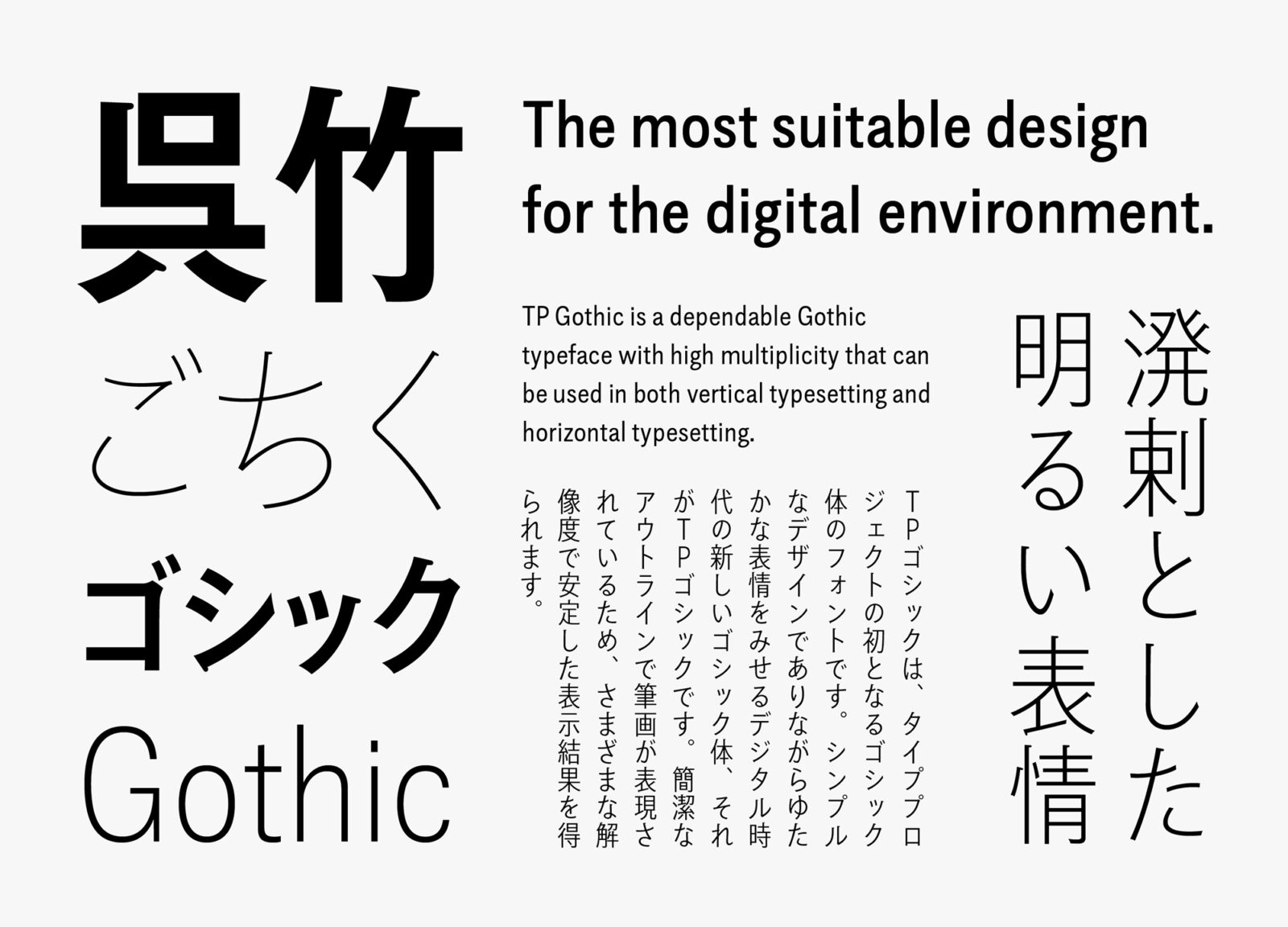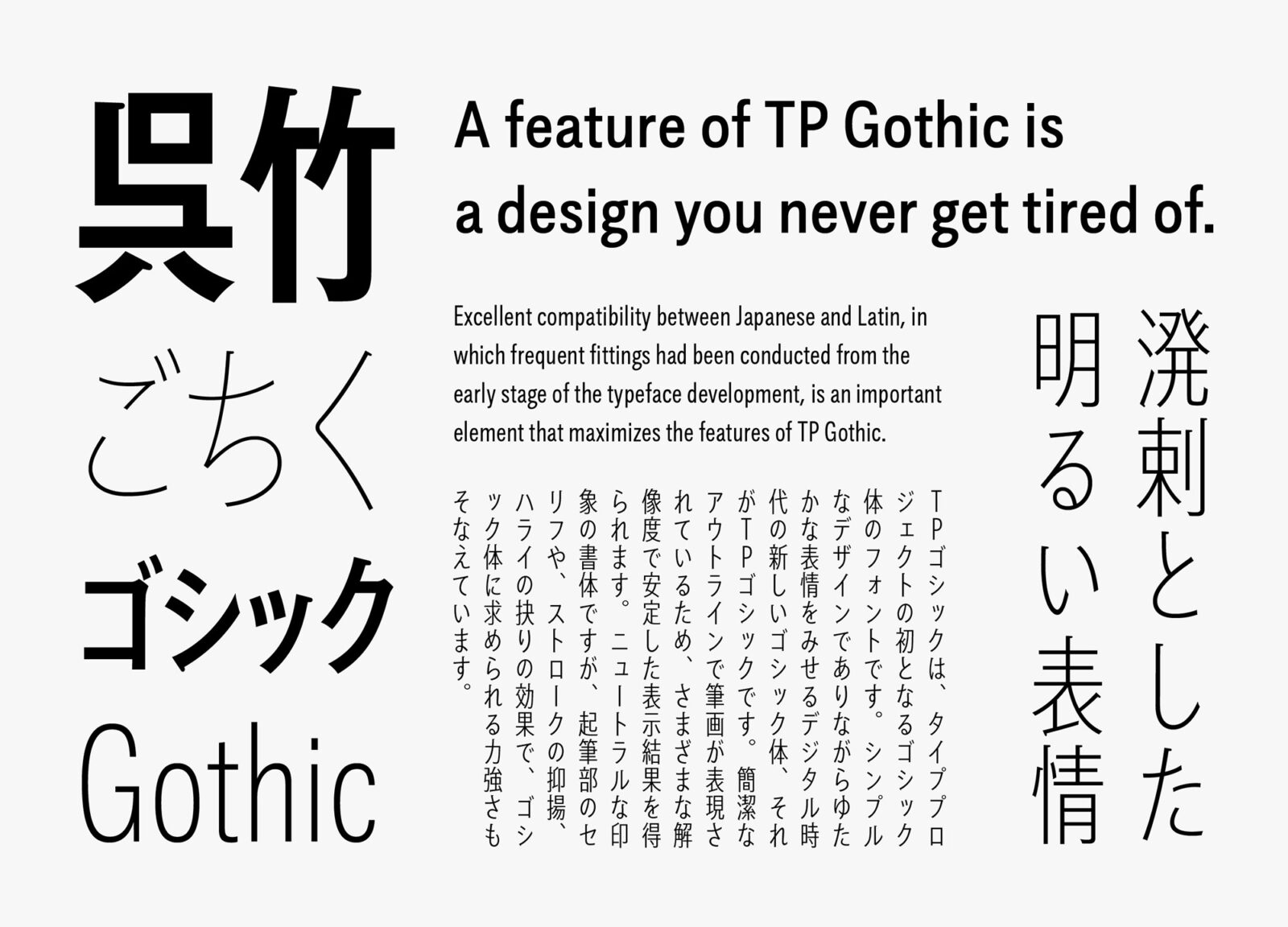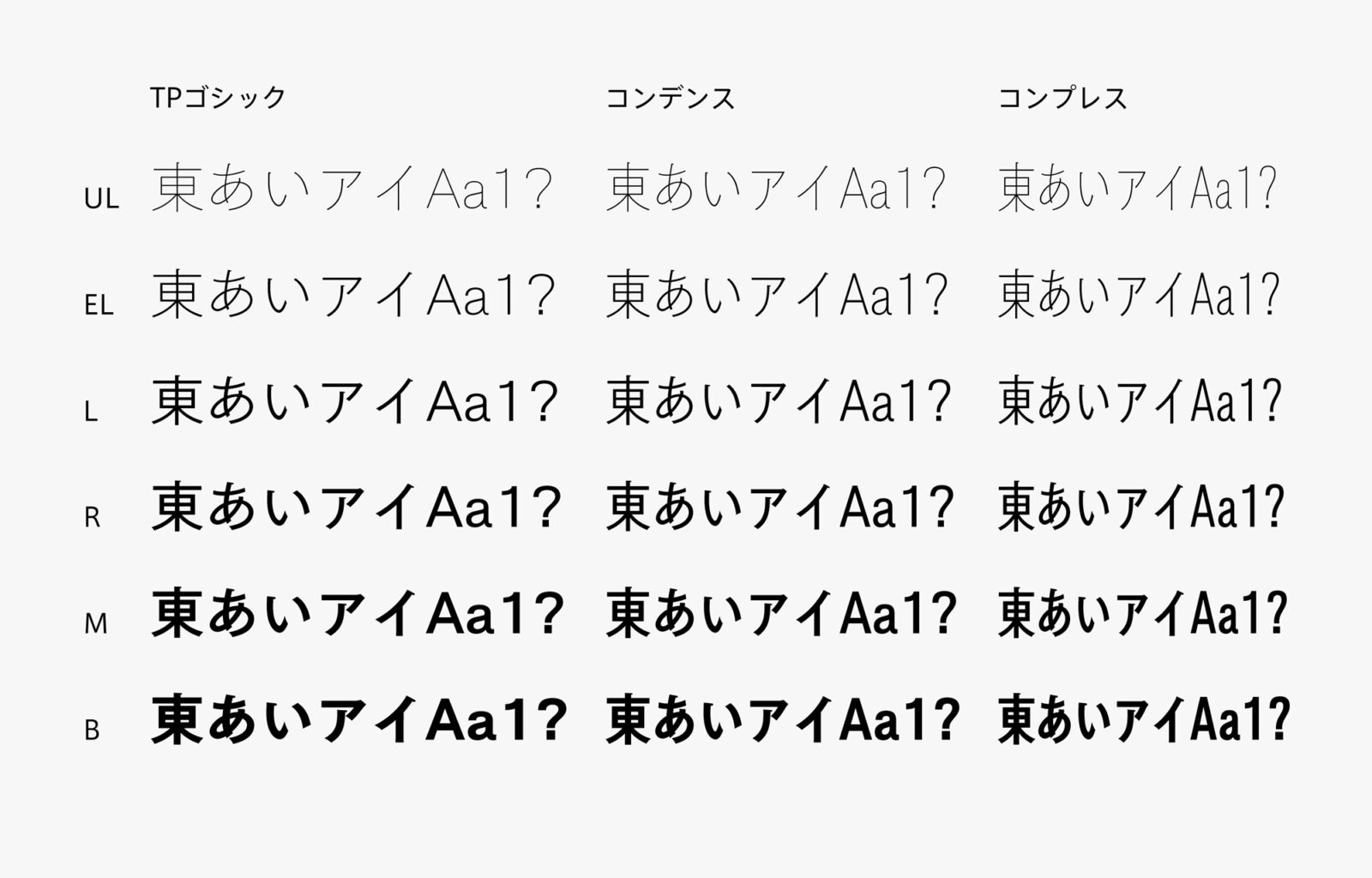
タイププロジェクト、「TPゴシック」の長体シリーズの提供開始
オーソドックスなデザインを継承したTPゴシック コンデンスとTPゴシック コンプレス
タイププロジェクト株式会社(東京都練馬区 代表取締役社長 鈴木 功)は、ゴシック体のフォント「TPゴシック」の長体シリーズ、「TP ゴシック コンデンス」と「TPゴシック コンプレス」を発表しました。本日よりタイププロジェクトのサブスクリプションサービス「TPコネクト」にて提供を開始いたします。
TPゴシックは、AXIS Font やTPスカイなどサンセリフ体を多く提供してきたタイププロジェクトの初となるゴシック体のフォントです。ゴシック体は見出し用途として、大きい文字サイズで使用されることが多く視覚的な歪みが目立ちやすい書体です。そこでタイププロジェクトでは、ゴシック体のカテゴリーにこそ字幅軸が必要と考え、TPゴシック正体のオーソドックスなデザインを継承した長体シリーズ、TPゴシック コンデンスとTPゴシック コンプレスを制作しました。
TPゴシック コンデンスとコンプレスは、長体に求められる省スペース効果を発揮するとともに、実用的な書体に必要な高い可読性を備えています。詳細なテストを行い、コンデンスは85%、コンプレスは70%の長体率で設定しています。TPゴシックは、コンデンスとコンプレスを加えてウエイトと字幅の二軸をもつ高性能なファミリーへと拡張することで、さらに汎用性の高い書体となりました。
また、落ち着いたオーソドックスなグロテスク系のサンセリフ書体である欧文は、x-height(エックスハイト)を少し高めにして文字幅を若干狭めに設定することで、欧文単体での読みやすさはもちろんのこと、引き締まったフトコロの和文との相性の良さを意識して設計しています。
タイププロジェクトの代表取締役 鈴木 功は、「長体でありながら自然な表情のゴシック体をつくるのは容易ではありませんが、AXIS Font やTPスカイで蓄積してきたスキルと知見を活かし、日本語長体ゴシックの決定版を目指した書体ファミリーです。欧文部も、正体のニュアンスを崩さずに展開することができました。正体TPゴシックの使い勝手の良さに長体ならではの省スペース効果が加わり、書体としての機能性が高まったことで、TPゴシックの活用シーンがさらに広がると思います」と述べています。
TPゴシック コンデンスとコンプレスは、正体と同じく、UL(ウルトラライト)、EL(エクストラライト)、L(ライト)、R(レギュラー)、M(ミディアム)、B(ボールド)の6ウエイトです。ULとELは、これまで培ってきた極細フォント制作の技倆を活かし、ユニークかつ完成度の高い書体に仕上げました。LとRは、長体であることを忘れてしまうようなナチュラルな表情のウエイトです。MとBは、TPゴシックの持ち味がよく分かるウエイトで、見出しに求められるゴシック体の役割をいかんなく発揮します。